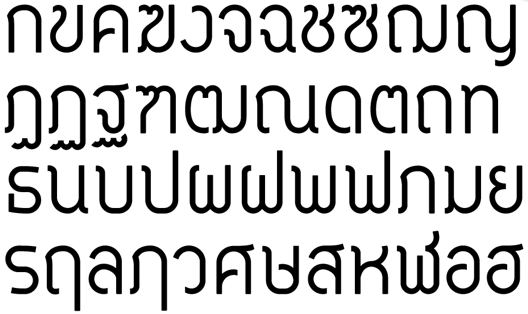
จริงๆก็คิดไว้นานแล้วว่าจะต้องเอากลับมาทำใหม่สักวันหนึ่ง
เหตุผลอื่นๆก็คืือ ผมหาฟอนต์ดิสเพลย์งามๆจะเอาไปทำงานช่วงทีสิธไม่ได้เลย
ก็เลยอยากให้ฟอนต์ตัวนี้เป็นดิสเพลย์ฟรีๆ ดีๆ ตัวหนึ่ง ( ฝันเยอะไปป่าวหว่า :08: )
ก็เลยแอบซุ่มทำไว้ แม้จะยังไม่เสร็จดี  :42:
ตอนนี้ผมเรียนจบแล้ว กำลังจะฟันฝ่าไปในเส้นทางสายนี้
ก็เลยคิดว่าจะเอามาปล่อยเป็นตัวส่งท้ายก็ละกันเนอะ  :52:
โครงสร้างเดิมๆคงไว้ เพิ่มเติมความเข้าชุดและการผ่อนปรนของระบบที่แข็งเกินไป
เหมือนเดิมครับ ติชมกันได้เลย  :12:
โว้วๆ  :25:
ชอบ ออ อ่าง กับ ฮอ นกฮูก  :22:
ช ช้าง ซอ โซ่ สวยดีครับ รอชมภาษาอังกฤษ กับ ตัวเลข
น่าใช้นะ ดูมันโปร่งๆ สบายตาดี
แต่ถ้าอ่านเร็วๆ ว. กับ ง. มันลักษณะใกล้เคียงกันพอสมควรเลยนะ
เมพว่ะเพื่อนผม !!!
ตัวนี้ไม่เอาอะ เดี๋ยวคุยยาว  :30: :30:
:07: อ๊าก สุดตีน
ตอนนี้ฟอนต์ฟรีของฟอนต์.คอมที่โด่งดังในแนวดิสเพลย์ก็คือ TP แทนคุณ
สงสัยตัวนี้จะเป็นตัวที่สองแน่ๆ ครับที่จะเห็นออกสื่อเต็มไปหมด
ชอบครับชอบ
แต่ลองพิจารณาปรับตัว ง งูอีกนิซนะ
(ดูคำว่า "จง" พอ่านแล้วมันสะดุดหน่อยๆ)
เกิดแล้วเพื่อนผม
ชอบจ้ะ ..
+ ให้กำลังใจ
เพิ่มเติมเลขไทย
เรียบหรู
อัพเดทเพิ่มเติมครับ
- แก้ ร เรือ ให้เข้าชุดมากขึ้น
- ภาษาอังกฤษ ( เทียบให้ดูกับตัวเก่า  :42: )
* เสร็จแล่ว ( รู้สึก metric ชิดไปนิด เดี๋ยวไปแก้เพิ่ม  :08: )
อัพเดทครั้งหน้า น่าจะได้ปล่อยแล้วครับ  :12:
ชุดภาษาไทย กับตัวเลขไทย เจ๋งมาก  :12:
เลขไทยส๊วยสวย :53: